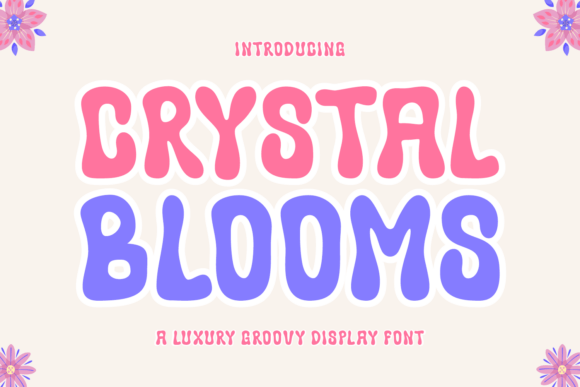
Crystal Blooms
์˜ฌ๋ฐ”๋ฅธ ๋””์ž์ธ ์š”์†Œ๋ฅผ ์ฐพ๋Š” ๊ฒƒ์€ ์–ด๋ ค์šธ ์ˆ˜ ์žˆ์ง€๋งŒ Crystal Blooms๋Š” ์ž‘์—…์„ ์ฆ‰์‹œ ํ–ฅ์ƒ์‹œํ‚ค๋Š” ๋›ฐ์–ด๋‚œ ์ปฌ๋ ‰์…˜์„ ์ œ๊ณตํ•ฉ๋‹ˆ๋‹ค.
์ •๋ฐ€ํ•˜๊ฒŒ ์ œ์ž‘๋œ Crystal Blooms๋Š” ๊น”๋”ํ•œ ๋ฒกํ„ฐ, ๋ถ€๋“œ๋Ÿฌ์šด ํƒ€์ดํฌ๊ทธ๋ž˜ํ”ผ ๋ฐ ์•ˆ์‹ฌํ•  ์ˆ˜ ์žˆ๋Š” ์ƒ์—…์šฉ ๋ผ์ด์„ ์Šค๋ฅผ ์ œ๊ณตํ•ฉ๋‹ˆ๋‹ค.
POD(์ฃผ๋ฌธํ˜• ์ธ์‡„) ์ œํ’ˆ, ๊ฒฐํ˜ผ์‹ ์ดˆ๋Œ€์žฅ ๋˜๋Š” ์†Œ์…œ ๋ฏธ๋””์–ด ๊ทธ๋ž˜ํ”ฝ์„ ๋งŒ๋“ค ๋•Œ Crystal Blooms๋Š” ์ด์ƒ์ ์ธ ์„ ํƒ์ž…๋‹ˆ๋‹ค.